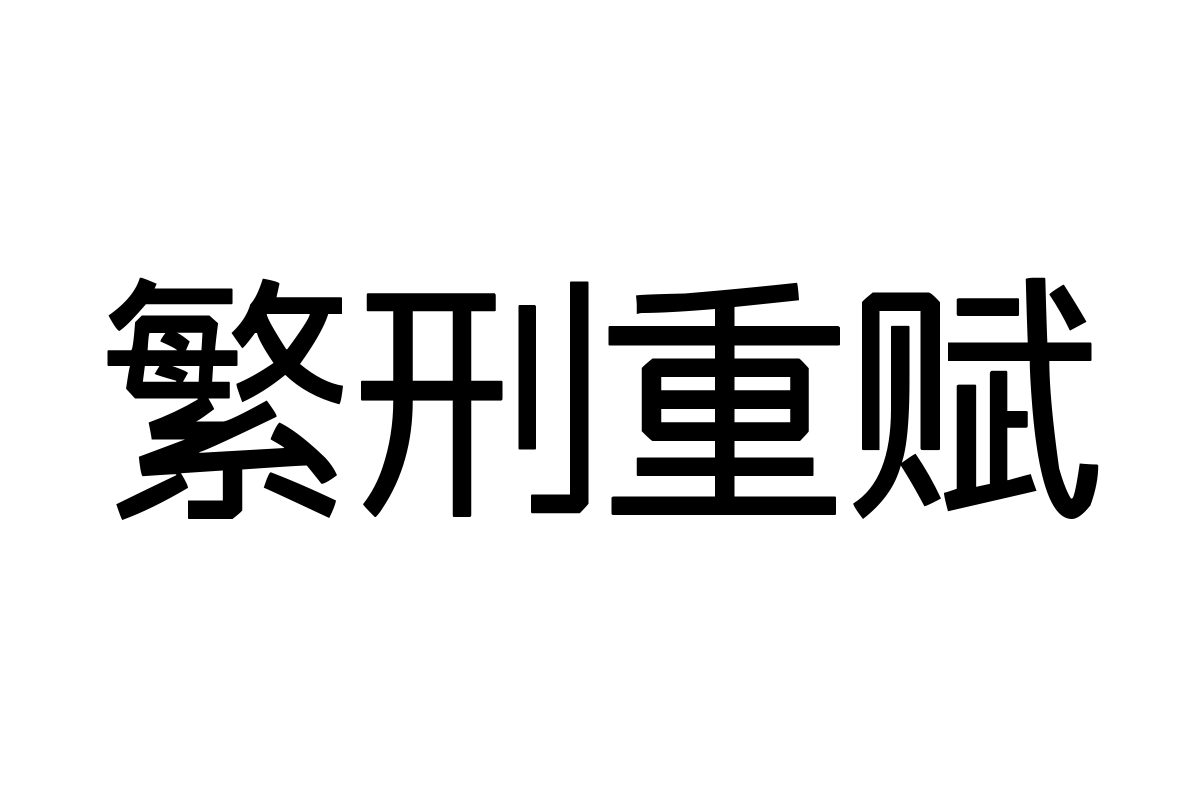
文道朗月黑字体是一种具有独特风格的现代中文字体,它以其简洁、流畅的线条和优雅的字形而受到广泛欢迎。这种字体的设计灵感来源于自然景观中的月亮和夜空,通过巧妙的笔画组合和排版设计,展现出一种宁静、祥和的氛围。
文道朗月黑字体的特点包括:
1. 线条流畅:该字体的笔画线条流畅自然,给人一种轻松愉悦的感觉。
2. 字形美观:每个字都经过精心设计,保持了良好的结构和比例,使得整体字形显得和谐美观。
3. 易于识别:由于其独特的风格,文道朗月黑字体在视觉上具有较高的辨识度,便于读者快速识别和阅读。
4. 适用范围广:该字体适用于各种印刷品和数字媒体,如书籍、杂志、报纸、网页等。
总之,文道朗月黑字体是一款具有独特魅力的现代中文字体,它的设计风格独特,线条流畅,字形美观,易于识别,适用于多种应用场景。